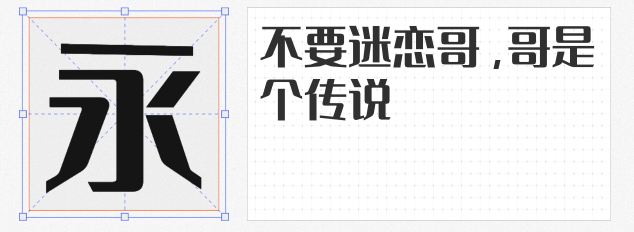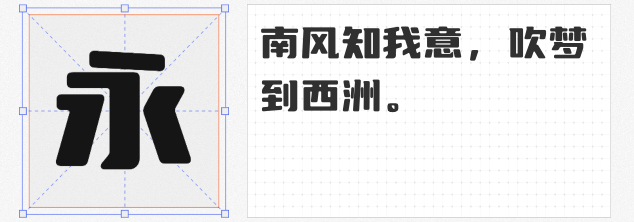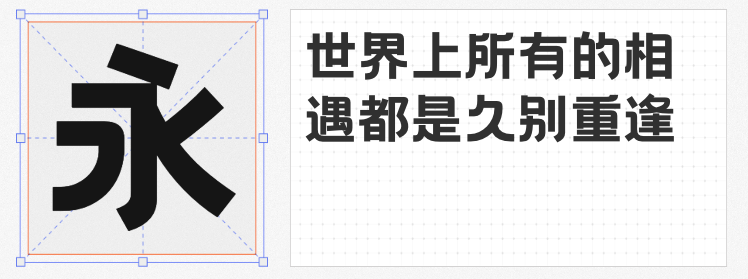
在设计的世界里,字体选择至关重要,尤其是标题字体,它能在第一时间吸引观众的注意力,传达出设计的核心信息。今天,将为大家推荐四款免费商用字库中的标题字体瑰宝,它们各具特色,适用于各种设计场景。
1、字由文艺黑
字由文艺黑,一款将图形设计法则巧妙融入黑体设计的字体。它通过优雅的艺术弧线处理,使得原本方正的黑体结构变得饱满而充满张力。这种设计不仅保留了黑体的稳重与清晰,更增添了一份文艺与灵动。无论是用于书籍封面、海报标题还是网页设计,字由文艺黑都能以其独特的韵味吸引人们的目光。
2、优设标题圆
优设标题圆,在优设标题黑的基础上进行了创新,将原本犀利的尖角转化为柔和的圆角。这一变化使得字体更加温和、亲切,适合用于营造轻松愉悦的设计氛围。无论是社交媒体广告、宣传海报还是产品包装,优设标题圆都能以其圆润的线条和舒适的视觉感受,赢得观众的喜爱。
胡晓波男神体2.0,一款字形设计阳刚又不失柔和的字体。其横竖笔画对比强烈,提笔走向规律,角度统一,字体边缘整齐。这种设计使得胡晓波男神体特别适合用于带有刚性的海报设计和标题设计,如科技、手机、汽车等领域的宣传。它能够准确地传达出产品的力量感和科技感,让设计更加引人注目。
4、阿里妈妈数黑体
阿里妈妈数黑体,一款兼具现代韵律与辨识度的字体。其字型饱满、体态中正,布白极具现代感。在“图形感”和“书写感”之间权衡得当,使得这款字体既能够正常阅读,又不失个性与辨识度。特殊的笔画处理更是让数黑体在字里行间流露出醒目、时尚和先锋的视觉感受。无论是电商平台的商品标题、广告横幅还是品牌宣传海报,阿里妈妈数黑体都能以其独特的魅力吸引人们的注意。
这四款免费商用字库中的标题字体,各具特色,适用于不同的设计场景。它们不仅能够提升设计的视觉效果,更能准确地传达出设计所要表达的信息和情感。希望这些推荐能够为您的设计工作带来灵感和帮助。